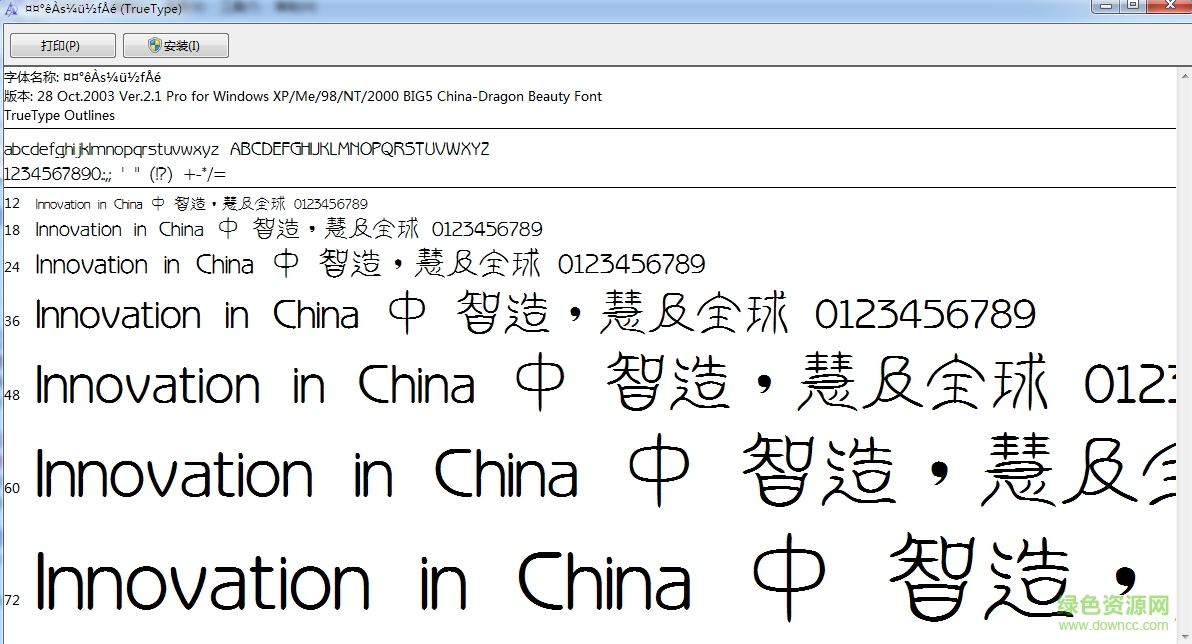
中國龍瑩篆體字體在同類字體中是比較受歡迎的一款篆體字體。不得不說使用這款字體輸出的文字效果非常的不錯!字體線條偏向于圓潤化,讓字體看起來不呆板!喜歡的用戶快來下載吧。
中國龍瑩篆體是一款非常有特色的電腦字體,根據(jù)中國古篆體制作而成,該字體線條粗細(xì)均勻,字形奇特但很有美感,看上去十分美觀,整體效果非常統(tǒng)一,有需要的朋友歡迎來綠色資源網(wǎng)下載!